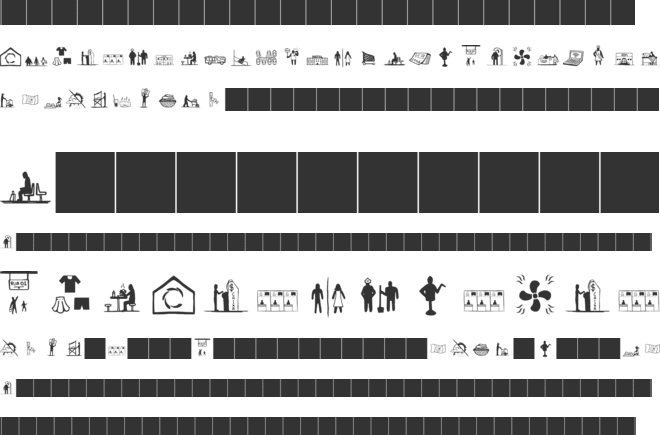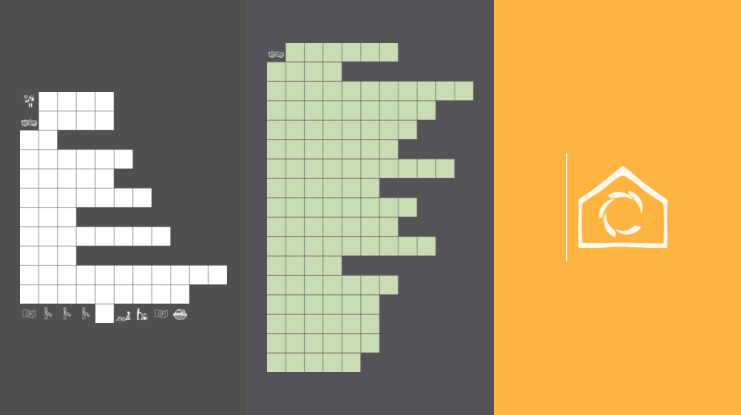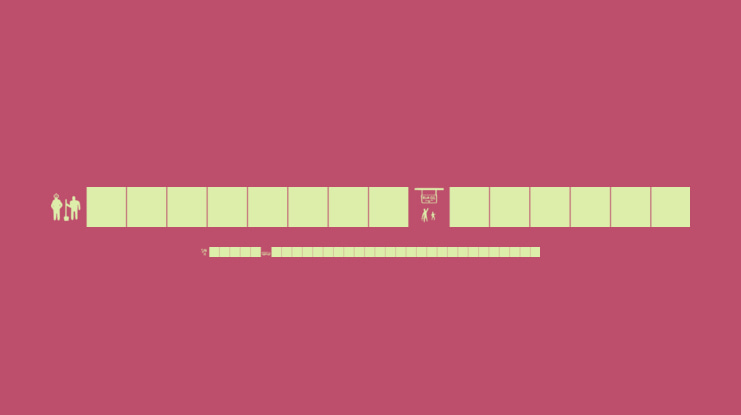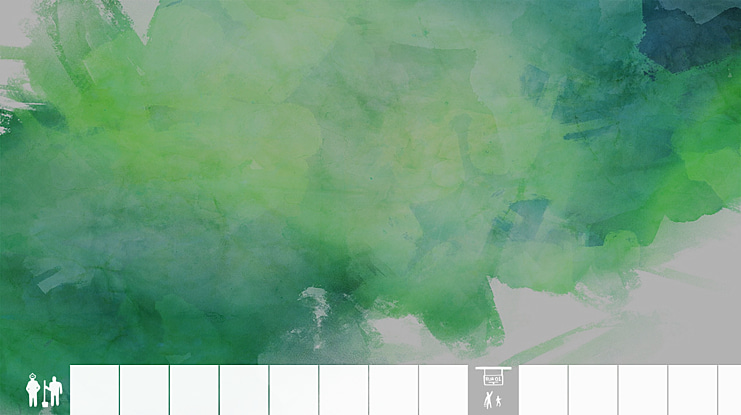
Feira da Sulanca Font
A Feira da Sulanca dingbats foi elaborada a partir dos elementos que mais caracterizam a feira da sulanca situada na cidade de Santa Cruz do Capibaribe, PE. Para isso foram feitos registros fotográficos e em seguida extraídos esses elementos para que fossem transformados em fontes.